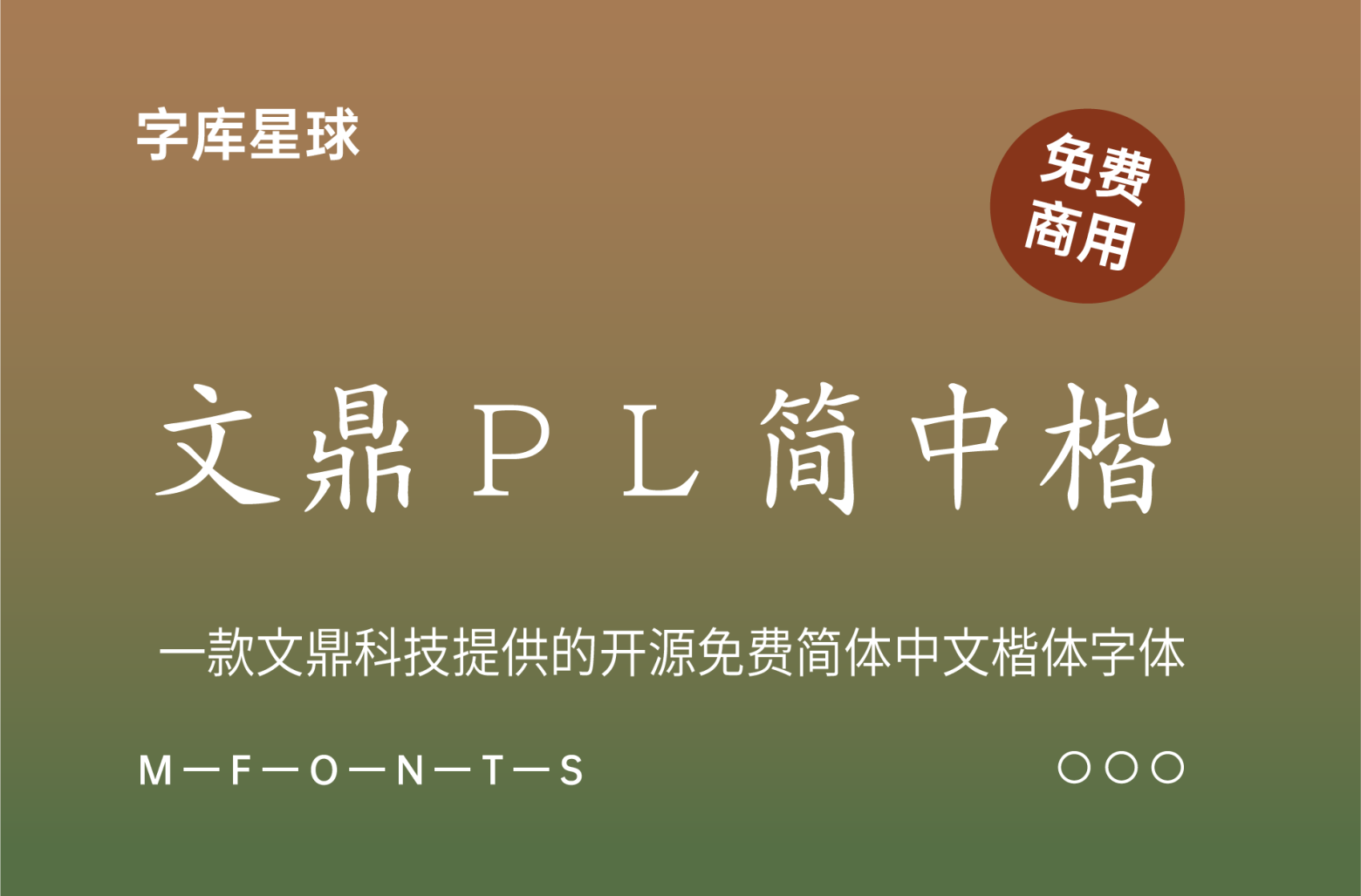
文鼎PL简中楷
文鼎PL简中楷是一款文鼎科技提供的开源免费简体中文楷体字体。
一款基于支持 Linux 与自由软件发展的立场, 文鼎科技热心的提供了四套开源免费中文 TrueType 字体(文鼎PL细上海宋、文鼎PL简报宋、文鼎PL中楷、文鼎PL简中楷)供大家自由使用,更可贵的是,该公司以类似 GPL 的版权释出字体、完全开放字体供人复制与修改,这种作为在目前软件厂商中是很少见的,这四套字体对整个中文环境的架构有很大的帮助。
冷知识了解一下:这款字体名称中的“PL”并不是指漂亮,而是代表这款字体是公众授权Public License。